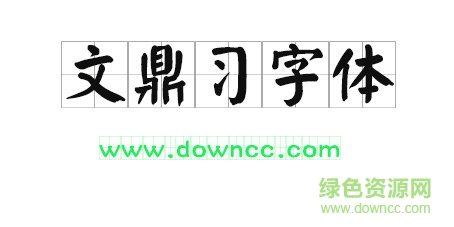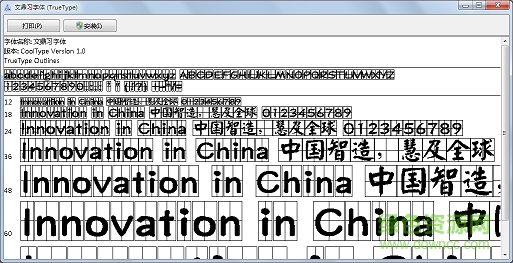
文鼎習字體是一款比較有個性的字體。該字體有個特點就是,輸入的每個字都會自帶方格效果,有種“小學生”寫字的既視感,這種字體也非常適合在字帖和書法練習中使用,變現(xiàn)的形式也非常的落落大方,不拖泥帶水,需要的用戶就來綠色資源網(wǎng)下載使用吧!
文鼎習字體別具一格,字跡飄逸灑脫,結(jié)構(gòu)寬松得體,行筆流暢而筆觸凌厲張揚,具有不錯的古風韻味,給你的平面設計、海報設計、包裝設計等帶來不錯的藝術體驗!